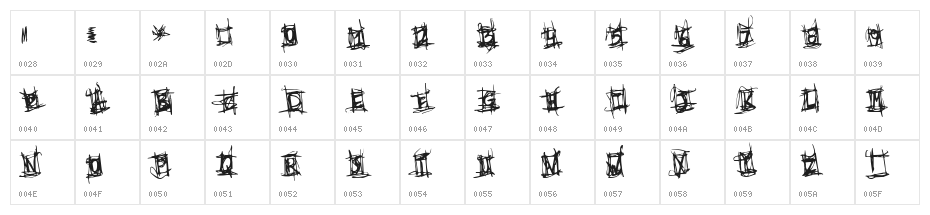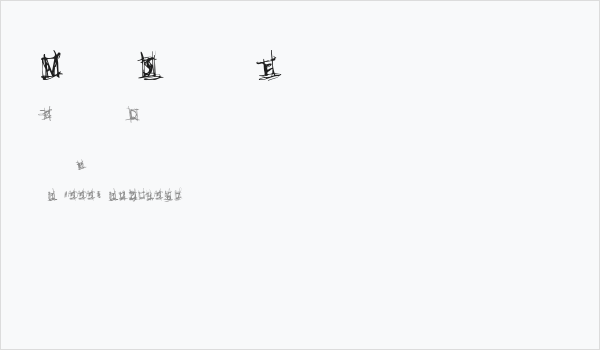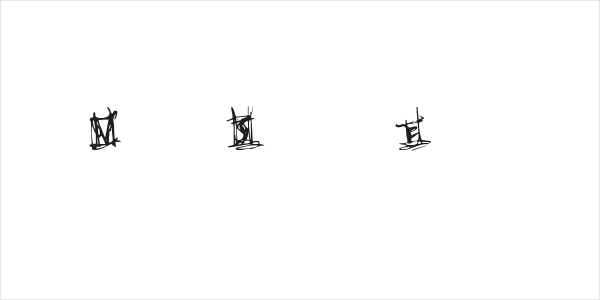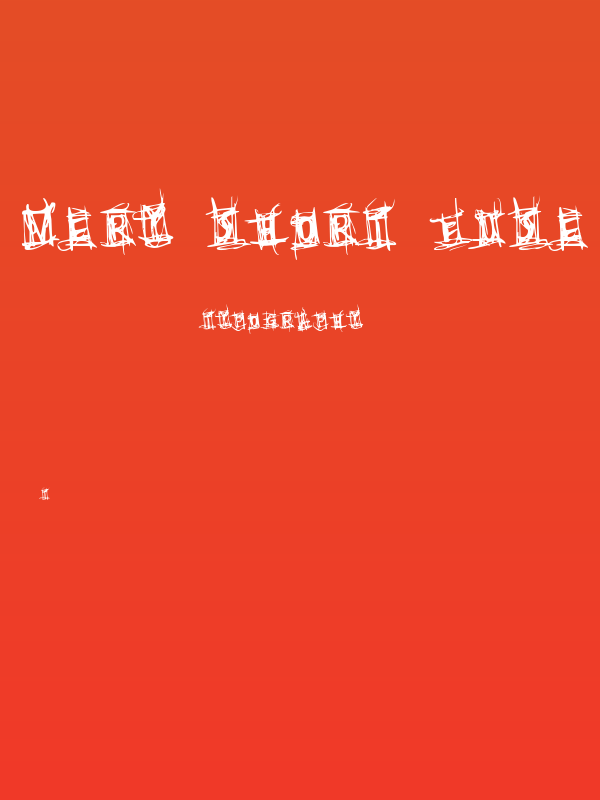
Very Short Fuse Font
| 分类 | Images & Symbols |
| 整体风格 | Modern, Artistic |
| 使用场景 | Logos, Posters, Album Covers |
| 推荐项目 | Ideal for edgy graphic design projects, album covers, street art-inspired posters, or any creative work that seeks to convey a sense of rebellion or artistic freedom. |